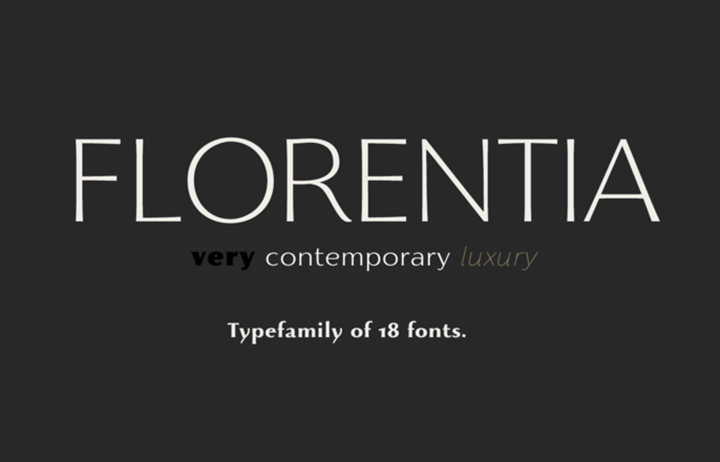
Agora que introduzimos mais uma herança do design épico de Hamilton para a ZetaFonts, apresentamos a Florentia Font Family, uma nova coleção de serifas e sans serifs que continua a tradição de alta qualidade dos outros projetos do designer. Inspirada nas formas majestosas da Beatrix, com seu modelo monumental romano, a Florentia incorpora influências profundas das esculturas em mármore do Santissimo Sacramento na catedral de Santa Croce em Florença. Embora baseada nos modelos antigos e tradicionais, essa fonte não se limita à simplicidade dos tempos passados. Ao invés disso, ela incorporou essas influências para criar um design mais contemporâneo, com uma altura X menor e um conjunto de caracteres extenso que abrange mais de quarenta idiomas usando o alfabeto latino, além de grego e cílindrico russo. Florentia é uma fonte perfeita para designers que desejam incorporar elementos clássicos no design moderno. Suas linhas simples e sua composição elegante permitem a criação de textos profissionais e bonitos, sem perder o charme e a tradição que acompanham as suas raízes históricas. Seja para um projeto em inglês ou para uma tradução multilíngue, a Florentia Font Family é uma escolha ótima para qualquer designer em busca de um equilíbrio perfeito entre o clássico e o moderno.